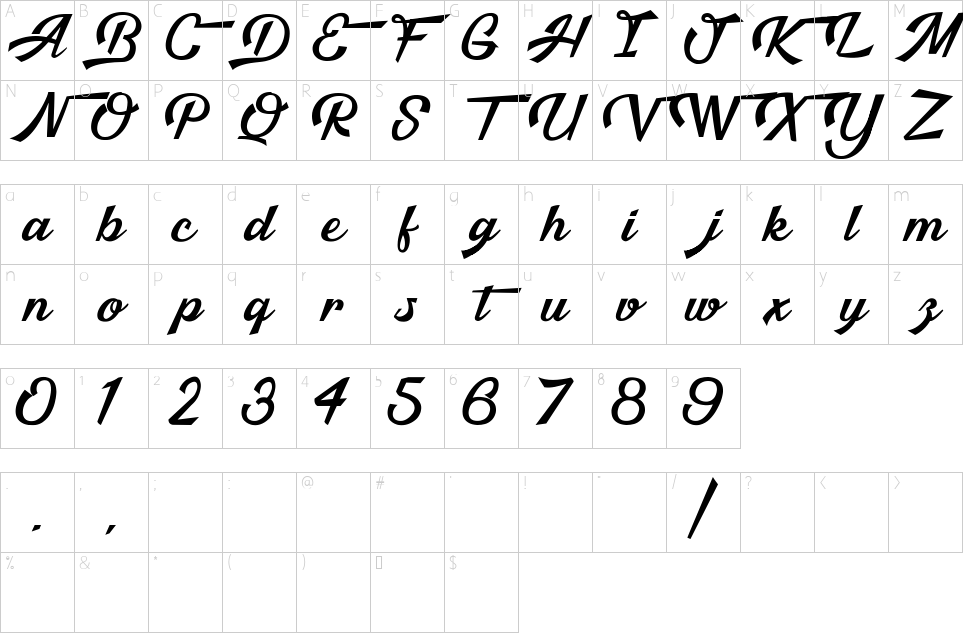
A fonte Malibu Babylon, desenvolvida pela Octotype, é uma ótima escolha para designers que procuram uma fonte com uma aparência fluida e versátil. Inspirada em estilos de gráficos antigos, essa fonte moderna traz um toque de clássico, ideal para trabalhos de design que exigem uma sensação de elegância e sofisticação. Com seu design minimalista e detalhes suaves, a Malibu Babylon oferece uma aparência moderna e versátil que se adapta perfeitamente a qualquer tipo de projeto, seja ele impresso ou digital. Para designers que valorizam a simplicidade e a elegância em suas criações, a Malibu Babylon é uma excelente opção. Com seu design limpo e elegante, é uma fonte perfeita para criar um visual sólido e confiável, sem perder o charme e a elegância que a Malibu Babylon oferece. A fonte já foi baixada 21,590 vezes, evidenciando o seu valor e importância na comunidade de designers.